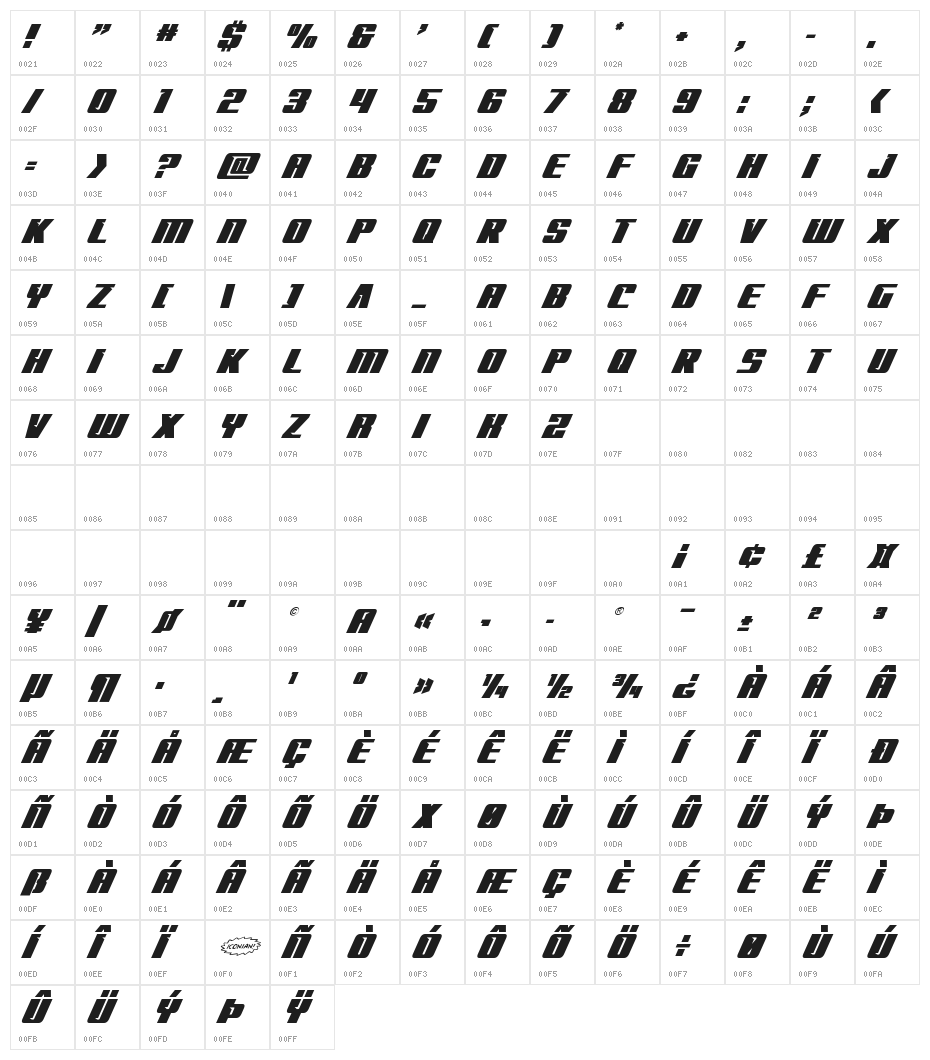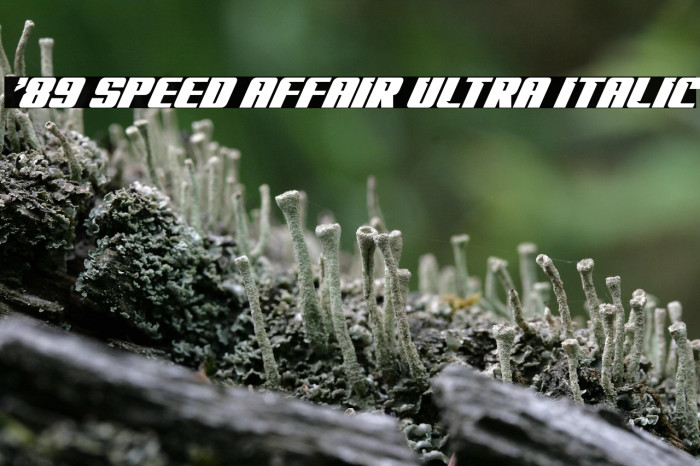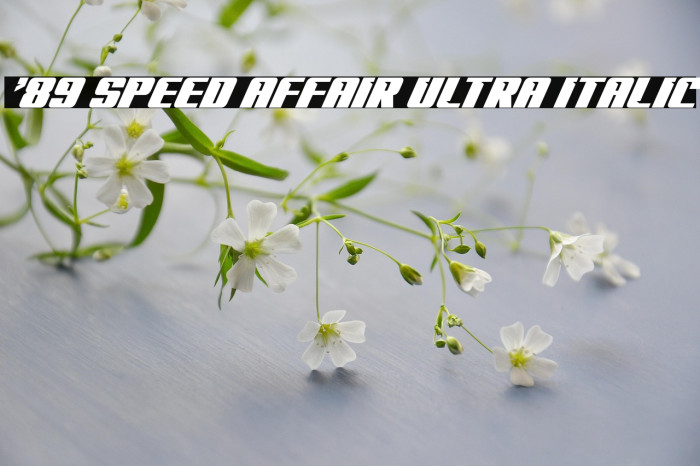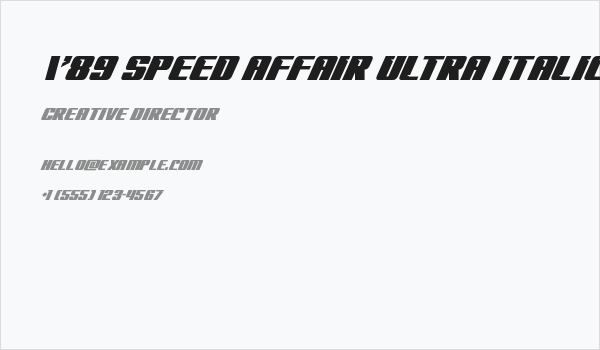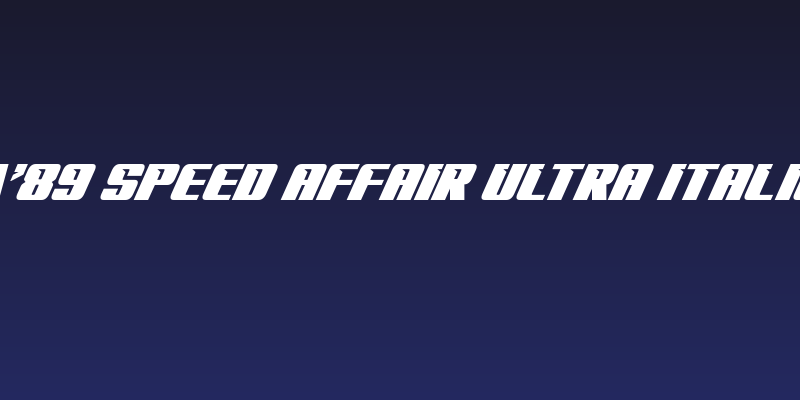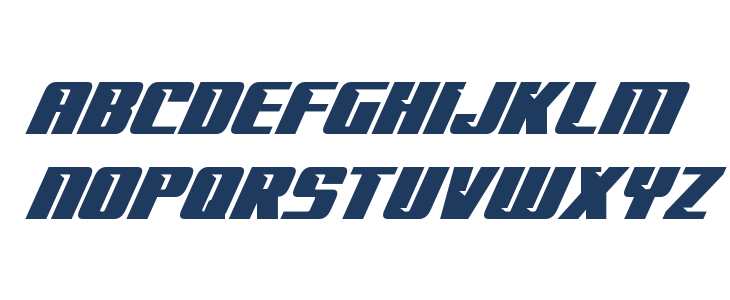
'89 Speed Affair Ultra Italic Font
| Progetti proposti | Ideal for sports branding, automotive advertisements, dynamic posters, and any project needing a sense of speed and energy. |